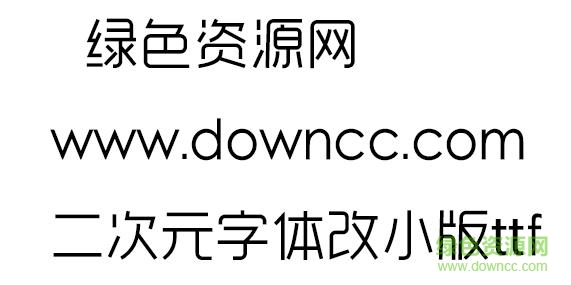
二次元字體改小版ttf為用戶們帶來(lái)了最美的二次元字體,這款通過(guò)不錯(cuò)的字體格式設(shè)計(jì)出來(lái)進(jìn)行了字體改小,讓你能夠感覺(jué)到更加不錯(cuò)的視覺(jué)效果,這款字體將能夠讓你運(yùn)用到眾多的行業(yè)中,同時(shí)也可以在二次元聊天彈幕制作以及字母制作過(guò)程中帶來(lái)不錯(cuò)體驗(yàn)!
用了一下二次元字體還是覺(jué)得縮小版的更有韻味,更喜歡這款字體,通過(guò)使用這款字體,小伙伴們都問(wèn)我要字體文件,真的挺好看的呢!